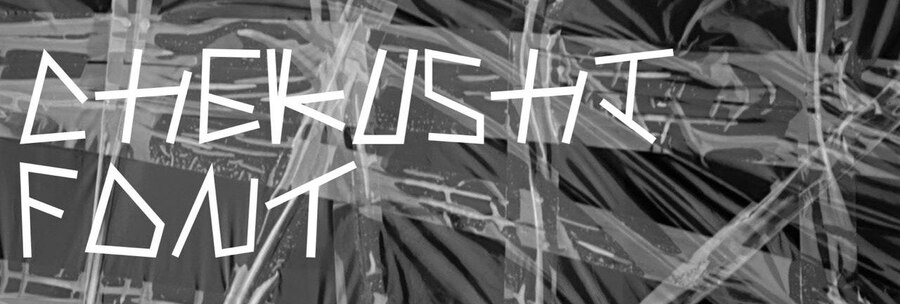
chekushi font
Chekushi — это модульный шрифт, вдохновленный узорами скотча на перемотанной рекламной вывеске.
структура
модульные линейки
кириллица
латиница
цифры и символы
шрифт в наборе
В процессе разработки шрифта я решила добавить альтернативную кассу кириллицы и латиницы с двойным штрихом у букв.
кириллица ss.01
латиница ss.01
Зин
карточки для Зина
развороты
флэт-план зина
Мерч